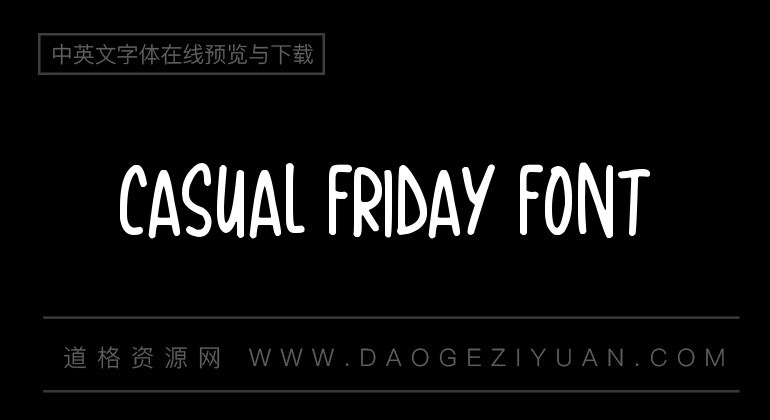
Casual Friday Font 是一种充满活力和轻松感的无衬线字体,适用于各种场合的设计项目。它的设计风格注重自然的手写感和流畅的线条,使得这个字体看起来非常灵动和有趣。 这种字体包含有大写字母、小写字母以及标点符号,支持多种语言,可以用于各种设计项目,比如海报、广告、包装设计、印刷品等等。它的轻松自然的风格使得它非常适合用于休闲和放松的场合,例如游戏、餐厅、咖啡馆等等。 总的来说,Casual Friday Font 是一种非常流畅,轻松和有趣的字体,适合在设计中使用以增加视觉吸引力和增强品牌形象。内容介绍
Casual Friday Font是一款非常不错的手写艺术字体,具有很好的视觉感,适合于文化类的宣传设计、商业类品牌的广告和产品包装设计以及个性化文字排版等较多场景。